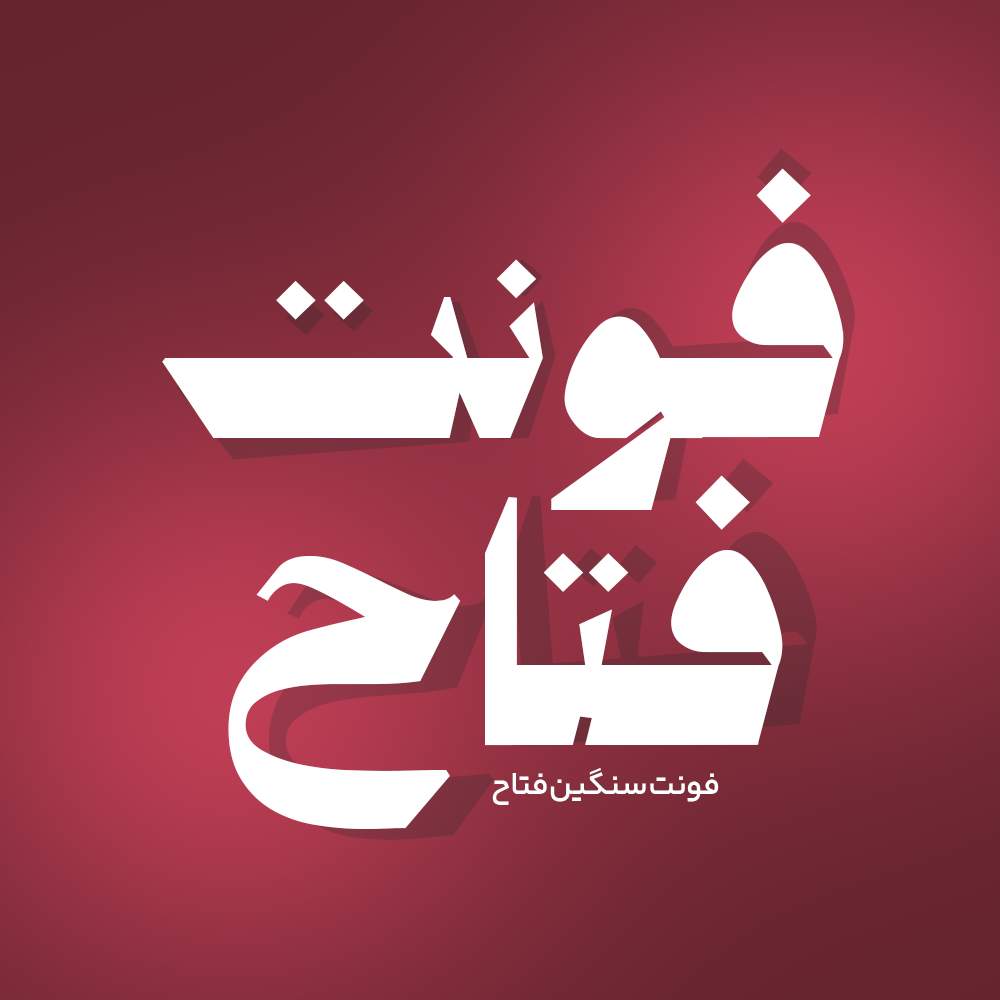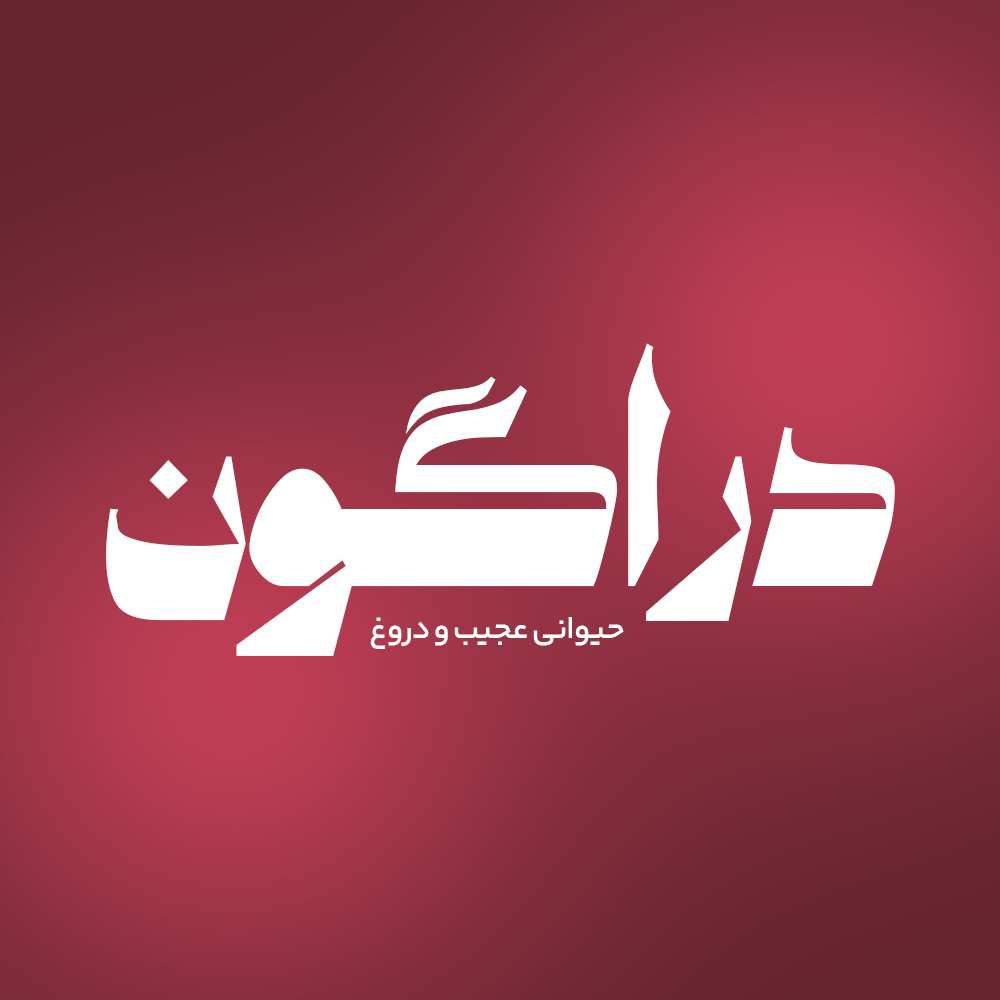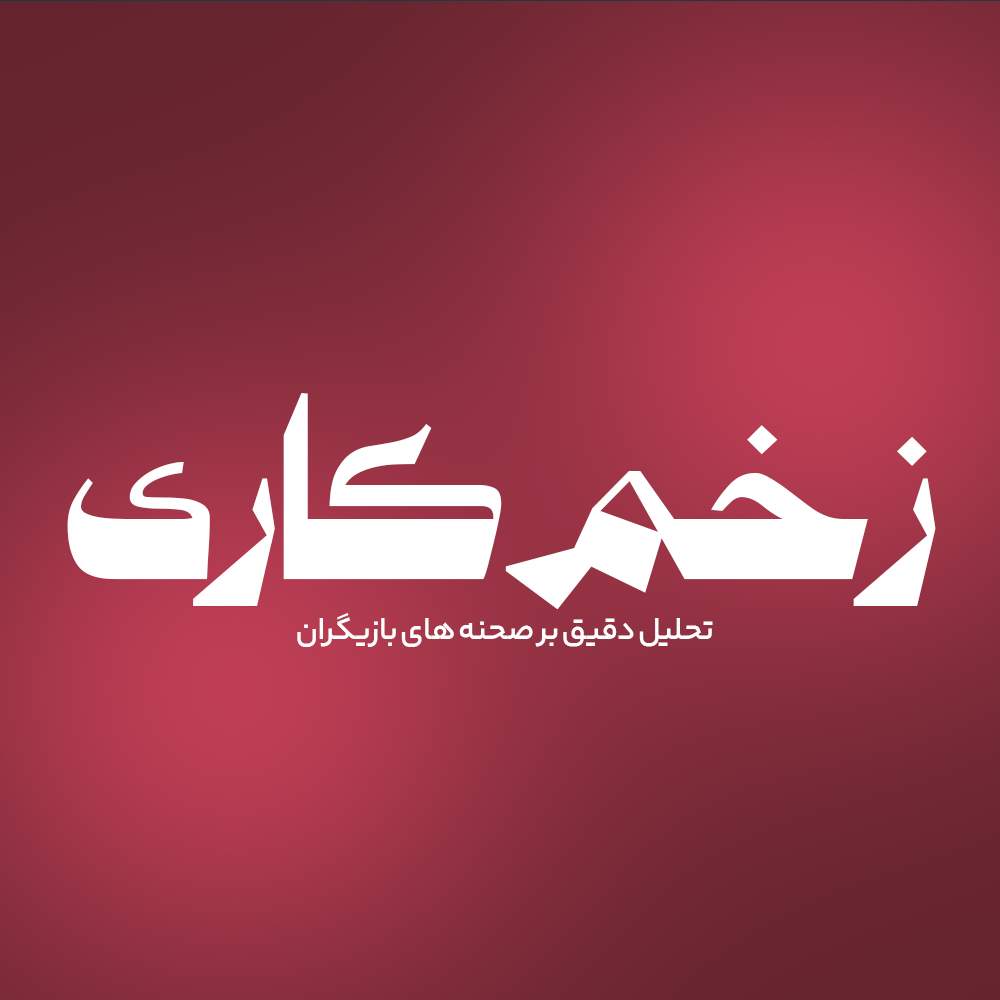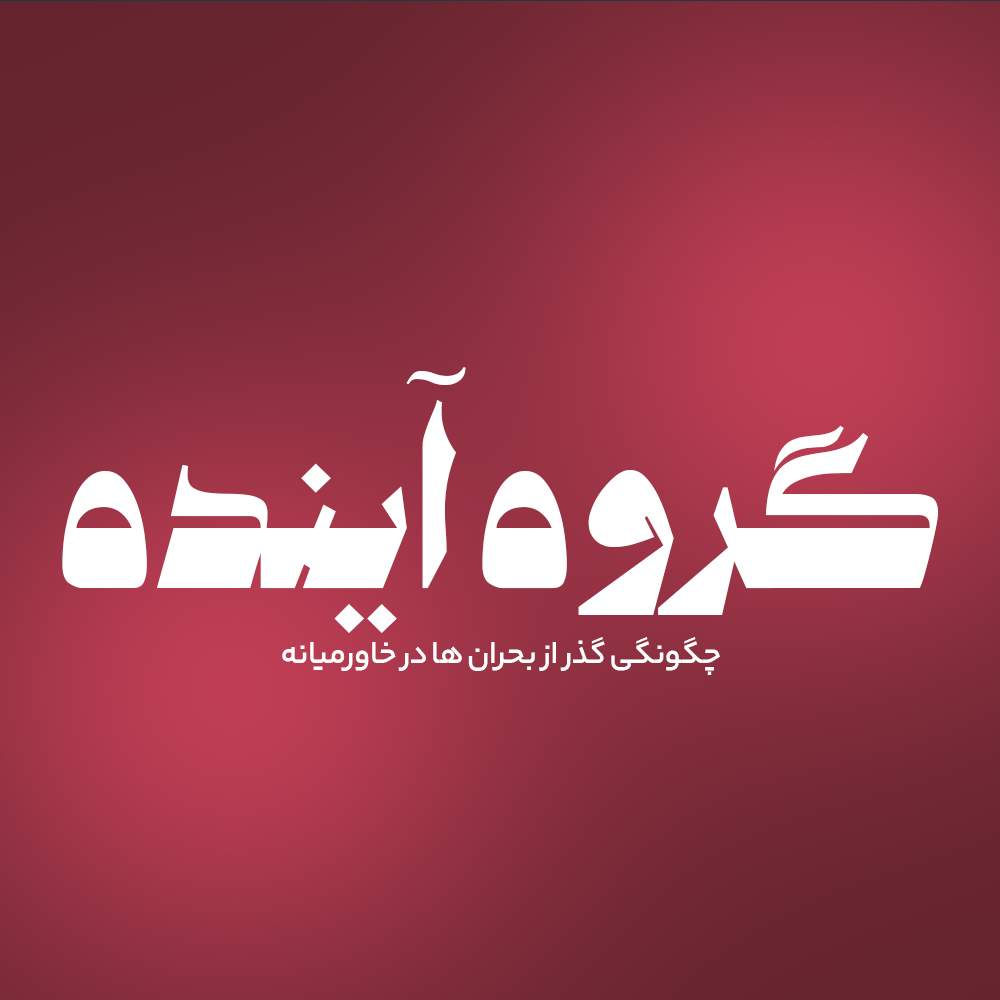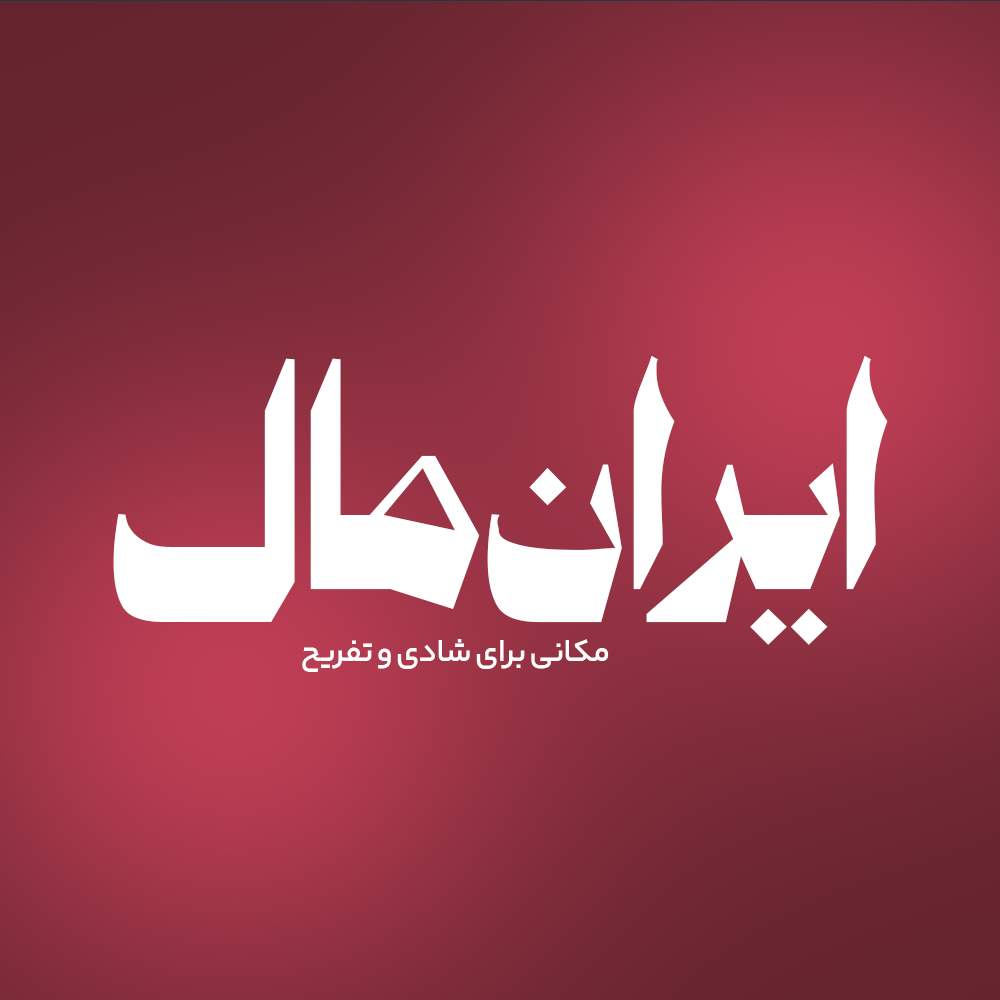
فونت فارسی فتاح Fatah Font
فونت فارسی فتاح از دسته فونت های هندسی است و اگرچه ظاهری ضخیم و بولد دارد اما پر انرژی و جذاب است. این فونت با ساختار…
فونت فارسی فتاح از دسته فونت های هندسی است و اگرچه ظاهری ضخیم و بولد دارد اما پر انرژی و جذاب است. این فونت با ساختار حروف خود مناسب استفاده در لوگوهای نوشتاری می باشد. همچنین از این فونت در طراحی تابلوهای چلنیوم هم به دلیل ساختار منحصر به فردش می توانید استفاده کنید. در ادامه برای شما نمونه تایپ های این محصول حرفه ای رو آماده کردیم که میتونید مشاهده کنید.
پیشنمایش و نمونه تایپ های فونت فتاح